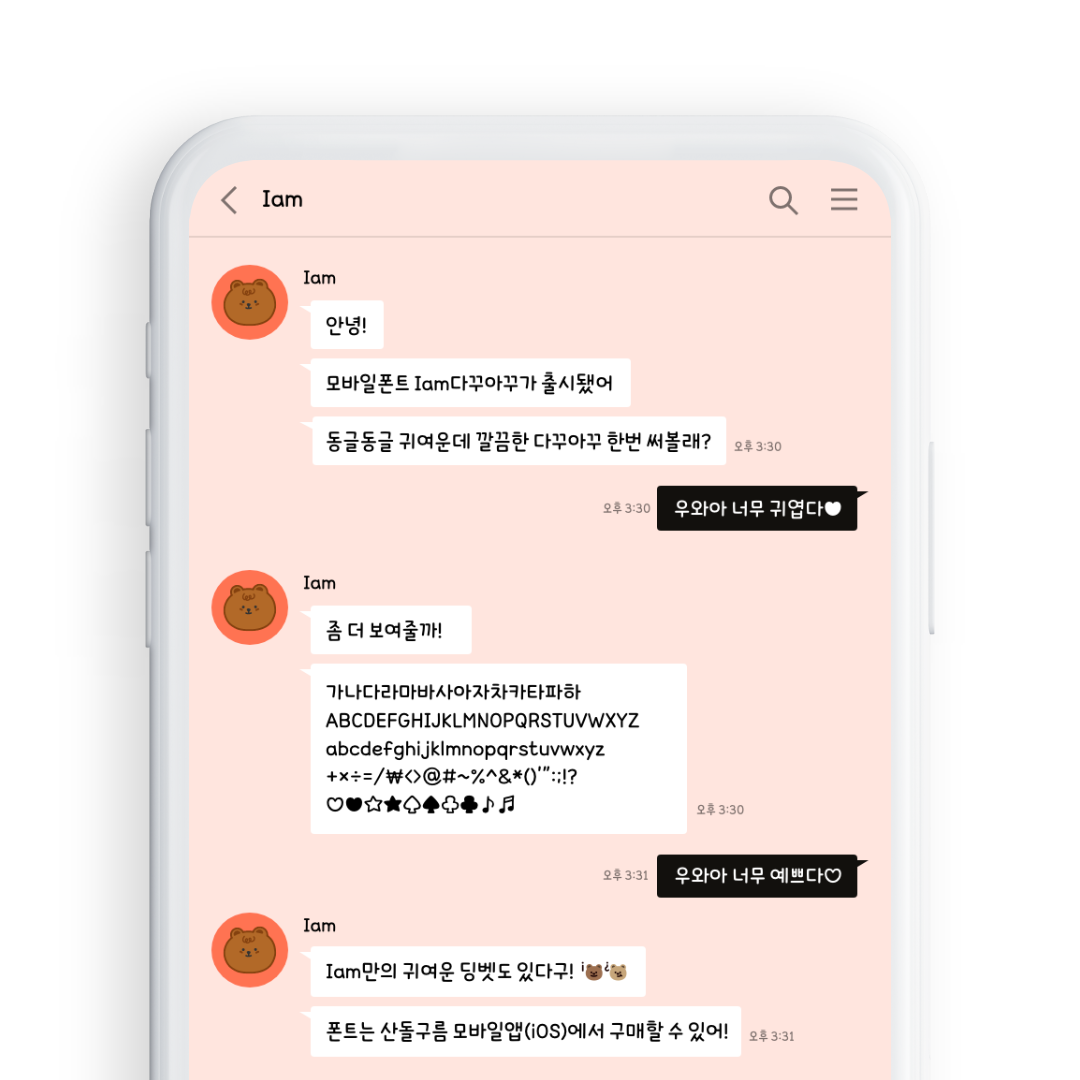
오늘 하루를 다꾸하면 기분이 좋아져!
다꾸아꾸는 동글동글 귀여운데 깔끔한 친구예요.
나만의 다꾸를 완성시켜줄 다꾸아꾸와 함께해봐요!
Iam 다꾸아꾸에는 귀여운 딩벳이 숨어있어요. 키패드에서 물음표와 느낌표를 꾹 눌러서 ¿ 역물음표와 ¡ 역느낌표를 타이핑 해보세요!
- Iam 다꾸아꾸 / Iam Dakku